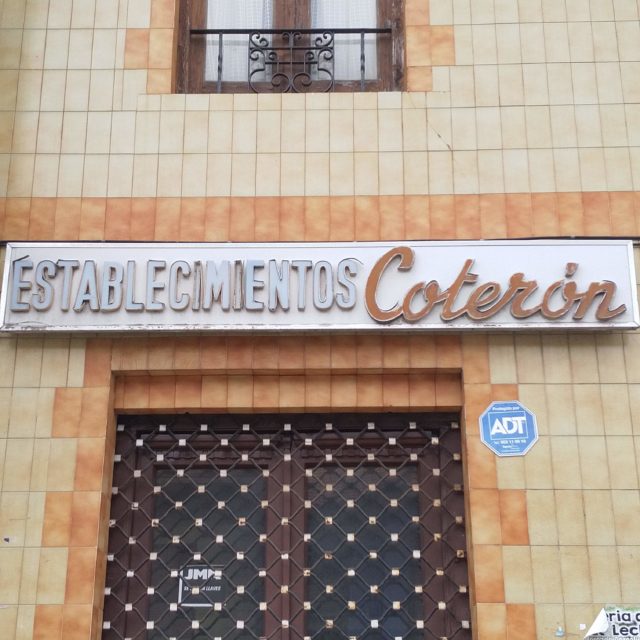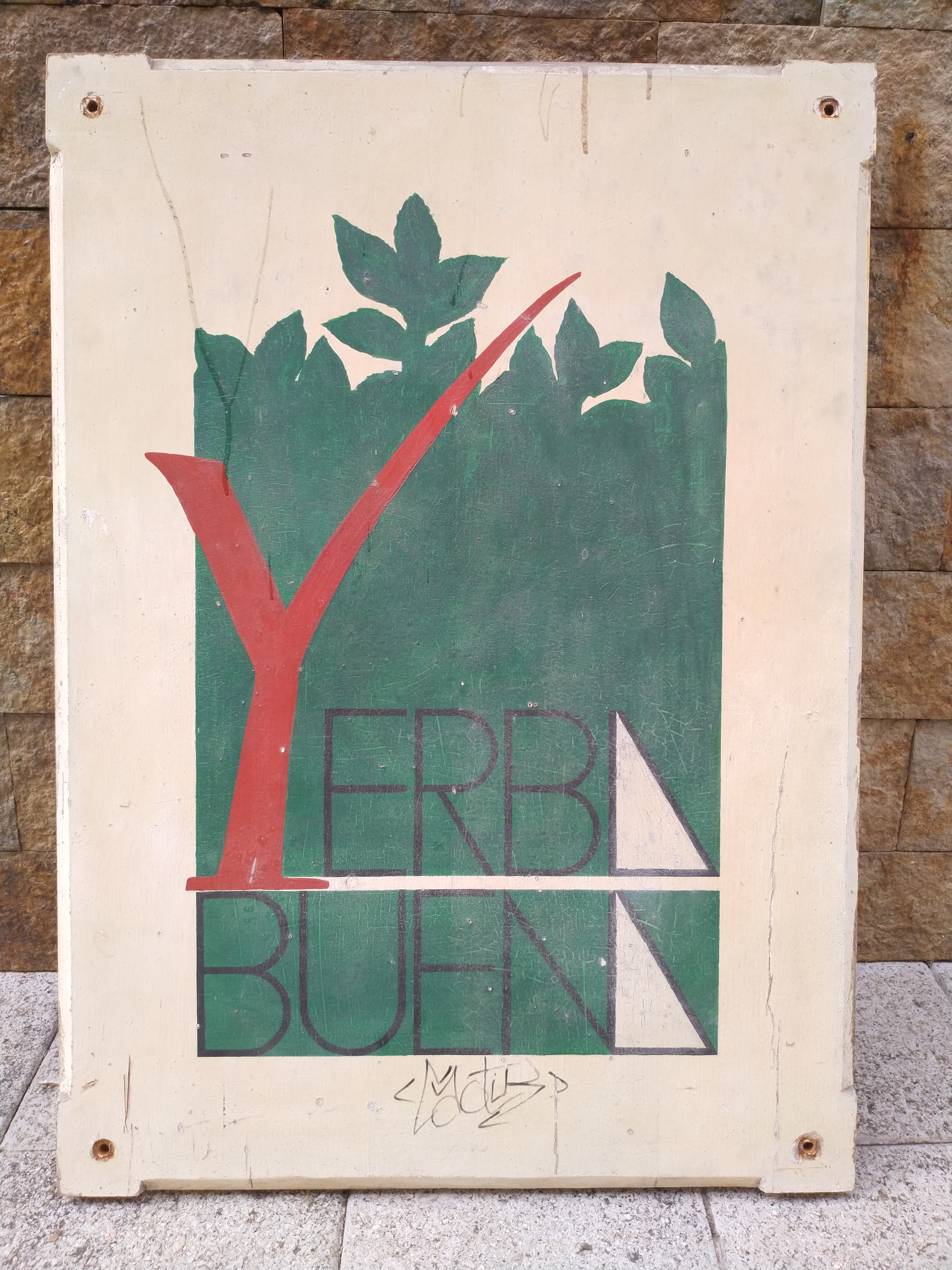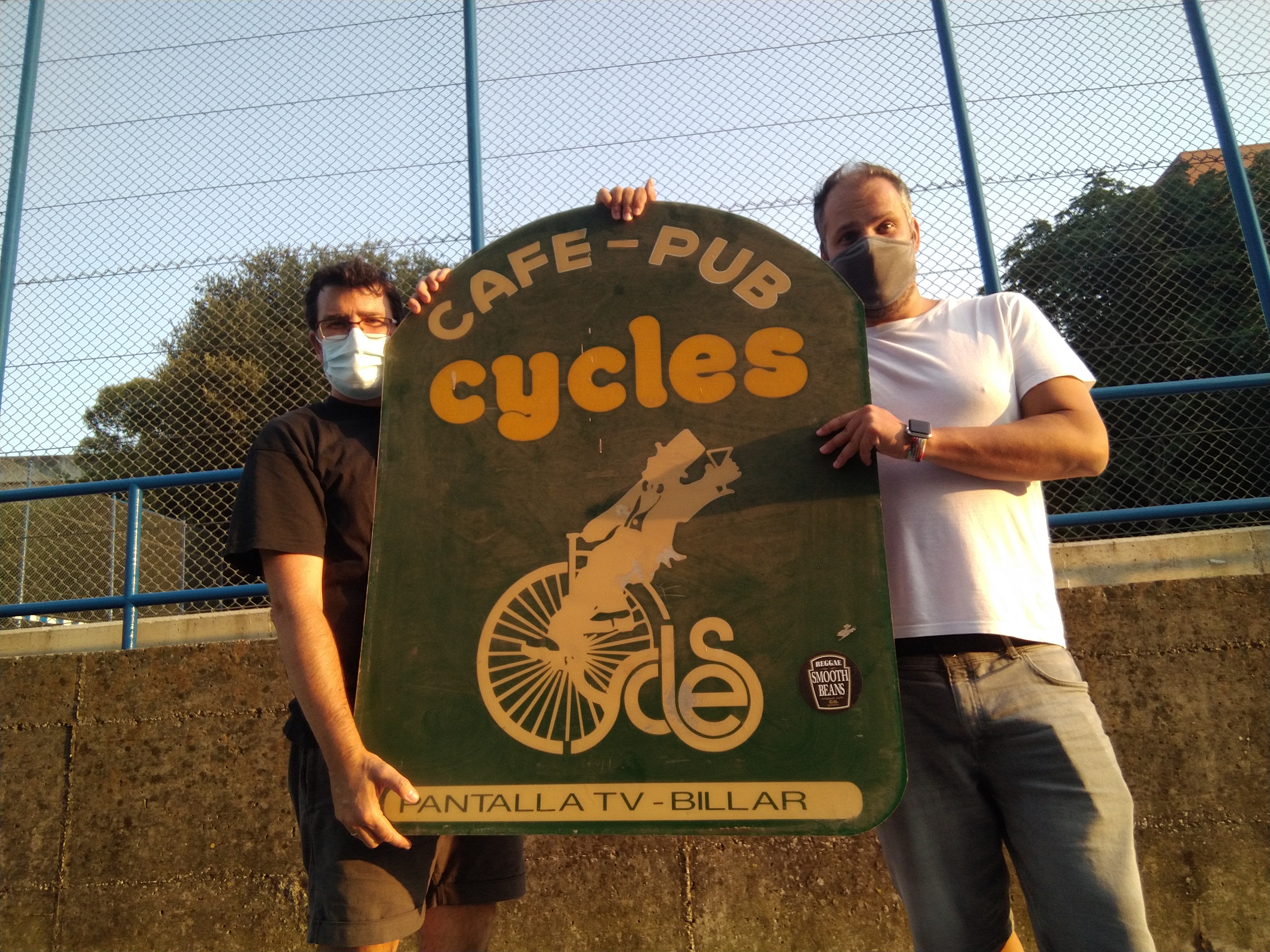
Nuestros rescates y preservación del patrimonio gráfico
Peluqueria Titos & Manuel
Esta semana hemos podido bajar los rótulos de esta emblemática peluqueria de barrio, ubicada en Hernán Cortés. Fue Manuel, uno de los propietarios, quien nos llamó para guardar uno de los rótulos, y el otro se lo quedará él. «Titos & Manuel» cerró el año pasado 2021, despúes de más de 50 años de actividad, y tras el fallecimiento de Titos y la jubilación de Manuel. Aunque los rótulos tienen más de 20 años, esta emblemática peluqueria ha sido conocida y querida en el barrio y en la ciudad, como así nos contaba Manuel. Para Santatipo es un placer y […]
Peña San Roque y Automóviles R. Jaen
La semana pasada, tras varios avisos de custodios de que estaban demoliendo el edificio y visitas a la obra, pudimos rescatar el rótulo de la “Peña San Roque”. El Patrimonio Gráfico también es aquello que hace barrio, y este era uno de esos carteles que estaba en General Dávila desde hace más de 40 años. Ahora queda preservado dentro del archivo del proyecto. Por otro lado, también el mismo día, pudimos recoger el cartel de “Automóviles R. Jaen”, por el comienzo de las obras de reforma del local, en la calle Tetuán. El negocio de importación de vehículos tenía cerca […]
Sonido 33/45
A finales de septiembre del año nos llegó un aviso de un custodio. Había aparecido el cartel de la mítica tienda de discos «Sonido 33/45» ubicada en la Cuesta del Hospital, 2. Tras un tiempo, y gracias a Roberto nuestro custodio, pudimos hablar con el propietario. Es Antonio, hijo de Antonio Perea quien regentaba la tienda. Después de contarle el proyecto, la filosofía y el objetivo de preservar ese Patrimonio, nos cedió tanto el cartel como algunas bolsas que aún tenía en su posesión.     Desde Santatipo, queremos agradecer a Antonio como su familia, la cesión de este pequeño […]
HornoPan y Ocean
Que mejor manera de comenzar el año con colaboraciones, recogiendo estos materiales que se han añadido al archivo del Proyecto y por tanto salvados de su desaparición: HORNOPAN: Estas letras estaban aún puestas en lo que fue el obrador de HornoPan que había en la calle Marqués de la Hermida, Santander. Gracias a la labor de una Custodia que conoce el proyecto, vio que se iniciaban las obras en el local. Nos avisó de que ya había apalabrado con la empresa de la obra que guardasen las letras. En cuando las bajaron, pudimos recogerlas y depositarlas en el local. OCEAN: […]
Salvados los cristales de la Mercería Canales
Esta semana hemos recogido los cristales de la vieja “Mercería Canales” en la calle Isabel II.  Fue de los primeros comercios abiertos en la nueva calle creada tras el Incendio de 1941. Cerró sus puertas en 2021. Aunque es un rótulo más moderno y vinilado, sustituyó hace varios años al original que desgraciadamente fue destruido por acabar roto y por el riesgo que suponía para los viandantes. Por fortuna, de ese, tenemos una foto de archivo gracias a la labor documental realizada entre los años 80 y 90 Jose Miguel Rodríguez Castillo, cuya parte del fondo ya tenemos digitalizado. Esta […]
Fotografia Capa
La semana pasada nos avisaron de que ya habían comenzado las obras en el local de esta tienda de fotografía que llevaba cerrada varios años. El actual propietario, nos llamó para ver si queríamos recoger los carteles y rótulo principal de la tienda. El viernes pudimos bajarlos y ahora quedan preservados junto al resto de rótulos que vamos salvando. De la imagen, destaca el uso de la tipografía manuscrita, que podemos entender era la del `antiguo propietario y fundador. Sobre «Fotografía Capa» no disponemos de muchos datos, por lo que nos gustaría pedir la colaboración de todos, para poder conocer […]
Salvado el rótulo de la confitería «La Góndola»
Tanto el rótulo original, como el cartel que había en el despacho de Cuatro Caminos quedaran preservados dentro del archivo del proyecto. El pasado 18 de octubre el cierre de esta mítica confitería Santanderina, de la cual eran famosos sus Roscos, pasteles y pastas. Fundada en 1957 por Luis Sánchez, con un obrador en la esquina de la Avenida Valdecilla, fue creciendo hasta tener un obrador ya en la calle Argentina, abriendo ya las tiendas de la Avenida Valdecilla y Cuatro Caminos. También estuvieron en la calle Lealtad. En este proceso también se suma la incorporación de sus hijos Jose […]
Rótulo de Neon de «Don Colchón»
Hace poco se pusieron en contacto con el proyecto para traer esta caja de Neón. Quien nos lo trajo fue Juan Ruiz, propietario de la tienda, que deseaba que fuese conservado. Resulta, que estaba guardada en un almacén y era necesario vaciarle. Gracias a las Redes Sociales y a la divulgación que hacemos desde el proyecto para la preservación de estos elementos, nos lo trajeron y ya forma parte del archivo y se suma a más de otra veintena de rótulos y carteles rescatados y salvados. Don Colchón Fundado en 1985 por Pedro, cuñado de Juan, y estaba ubicado en […]
Salvada parte de la gráfica de los Cines de Peñacastillo UCC
Corría el año 2000 cuando se inauguraron estos cines en el Centro Comercial Peñacastillo, de Santander. Uni´ón Cine Ciudad se instalaba con 12 salas ampliando la oferta en la región de Multicines, especialmente en arco de la Bahía. Era el tercer Centro Comercial en Cantabria que incorporaba el cine a sus instalaciones; antes en 1995, fueron los Cines de Vallereal y 1999 Cinesa. En 2002 cerraría definitivamente El Capitol en Santander. Después de más de 20 años y tras la pandemia, en mayo de 2021, cerrarían definitivamente sus puertas. Desde el proyecto, seguimos de cerca la evolución y en 2023 […]
Salvado el cartel de «Pan de Ojaiz»
La casualidad quiso que pudiéramos recoger este cartel, ya un icono de la N-611 en Ojaiz. En cuestión de horas, tanto el edifico como el obrador, que ya tenían más 50 años desaparecieron. El inminente inicio de obra y el pasar en ese momento han sido los factores de poder salvar este pedazo de historia.